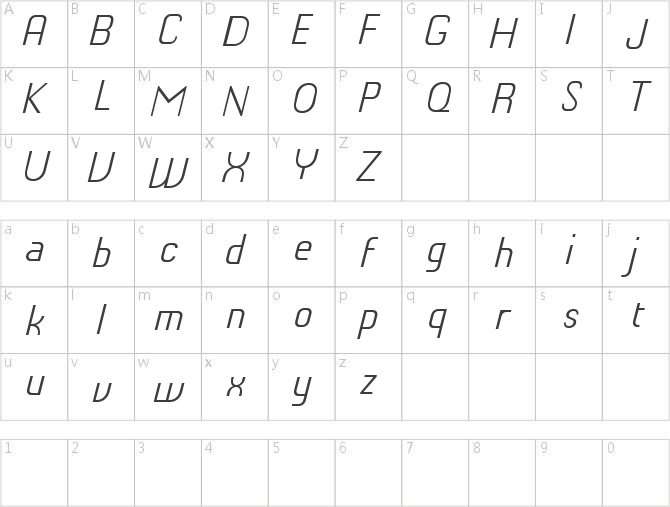
Chiq_Reduced_LightItalic 詳情頁
字體名稱: Chiq_Re
Chiq_Reduced_LightItalic
Chiq_Reduced_LightItalic字體字庫是一款讓人賞心悅目、百看不厭的英文字體,適合各類廣告和產(chǎn)品包裝設(shè)計應(yīng)用,字體大小0.02MB,格式為ttf字體,上傳用戶是昊天金誠,作者/版權(quán)方為未知